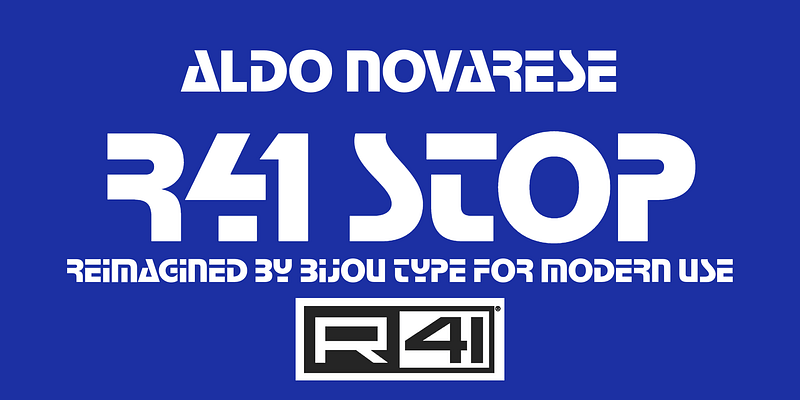
„Es ist die meistdiskutierte und meistkopierte Schrift der internationalen Grafikszene. Sie eröffnete neue Wege zur Vereinfachung des alphabetischen Zeichens der Zukunft. Einige Buchstaben sind trotz ihrer Halbierung im grafischen Kontext sehr gut lesbar. Sie wurde nicht nur für die Komposition phantasievoller Sätze, sondern auch für Markenzeichen, Akronyme, Schilder und Insignien entwickelt.“ – Aldo Novarese. Für diese neue digitale Version von Stop für R41 war es wichtig, sich von der ursprünglich hergestellten Trockentransferschrift inspirieren zu lassen. Diese neue Version von Stop basiert auf den für die Version von R41 vorbereiteten Folien, wurde dann aber mit vielen weiteren Zeichen versehen, die das Konzept erweitern, darunter eine Vielzahl von diakritischen Zeichen, Symbolen und Buchstaben für das kyrillische und griechische Alphabet. R41 Stop enthält außerdem OpenType-fähige Alternativen für viele seiner Buchstaben, basierend auf Anpassungen, die im Laufe der Jahre von Designern und Schildermalern weltweit vorgenommen wurden.
Reber R41
Die Aldo Novarese-Sammlung
Die bekanntesten Schriften des legendären Nebiolo-Schriftanbieters in Turin, entworfen von Aldo Novarese, auf der Grundlage ihres Original-Designs digitalisiert und absolut authentisch.